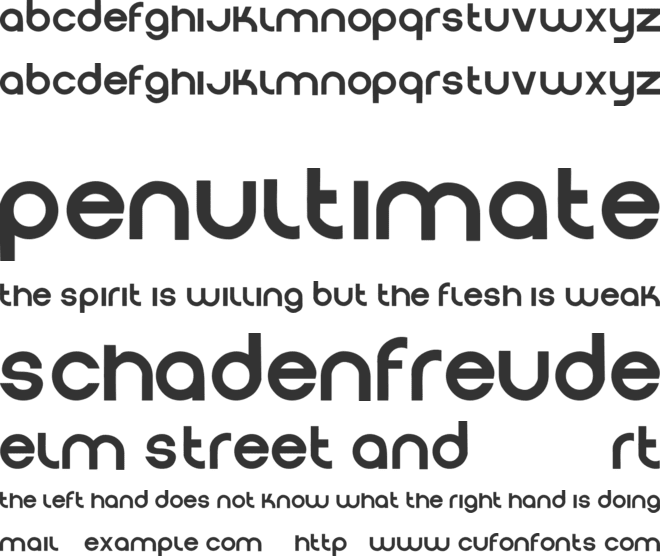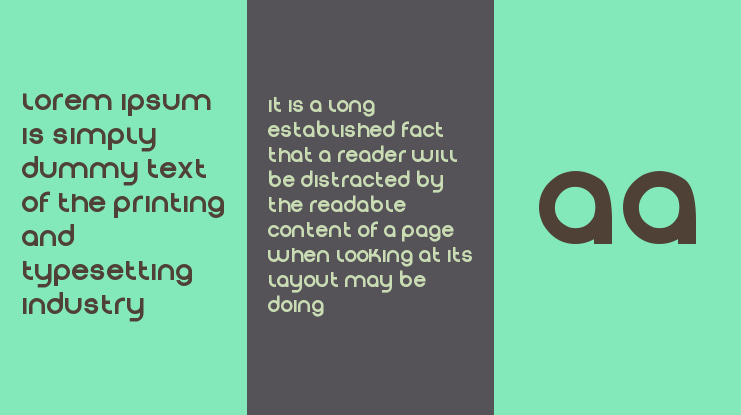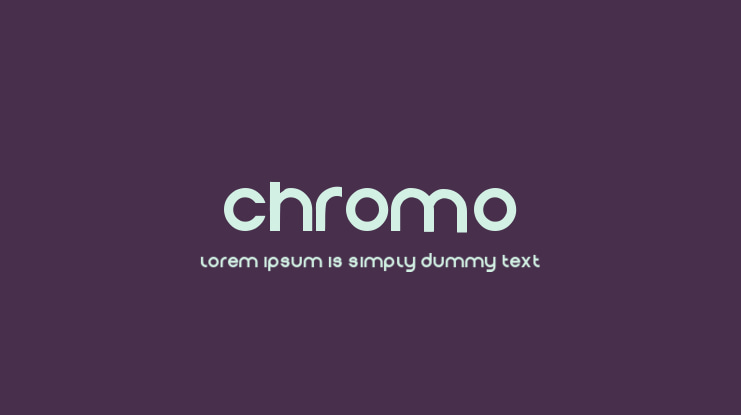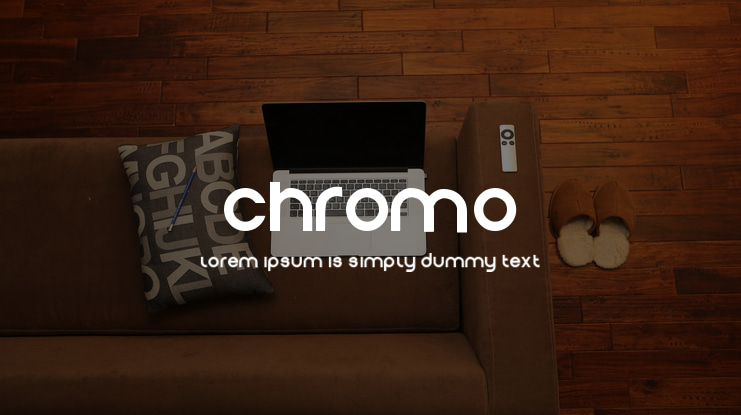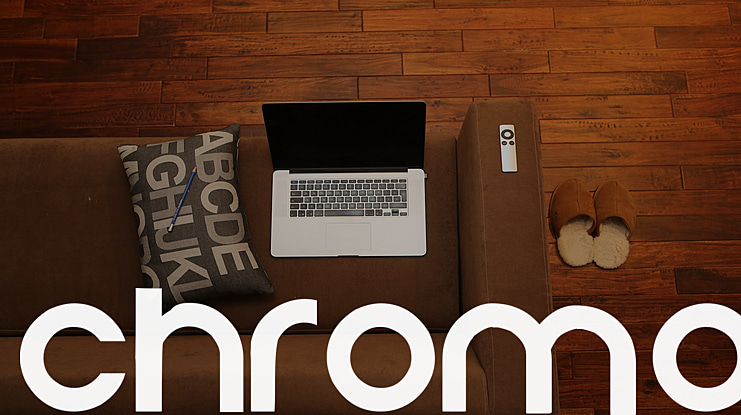
Chromo Font
Chromo es una fuente redondeada creada por TEARINGFONTS (FontStudio-LAB), ademas esta fuente esta completa para que la uses ya sea en tu negocio, logo, marca de tu canal de YouTube etc.